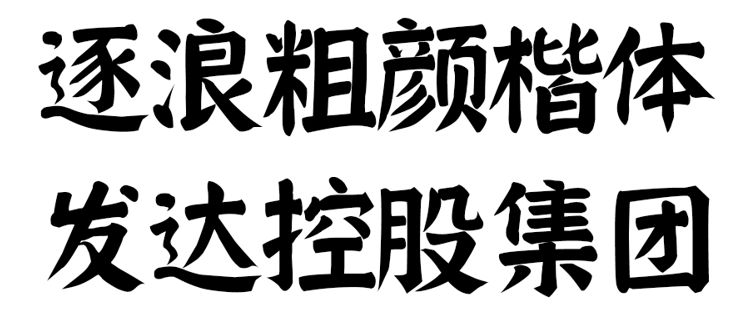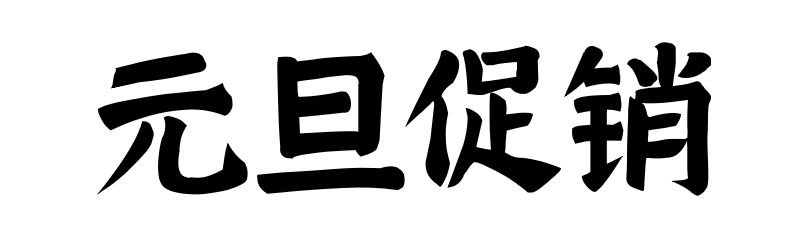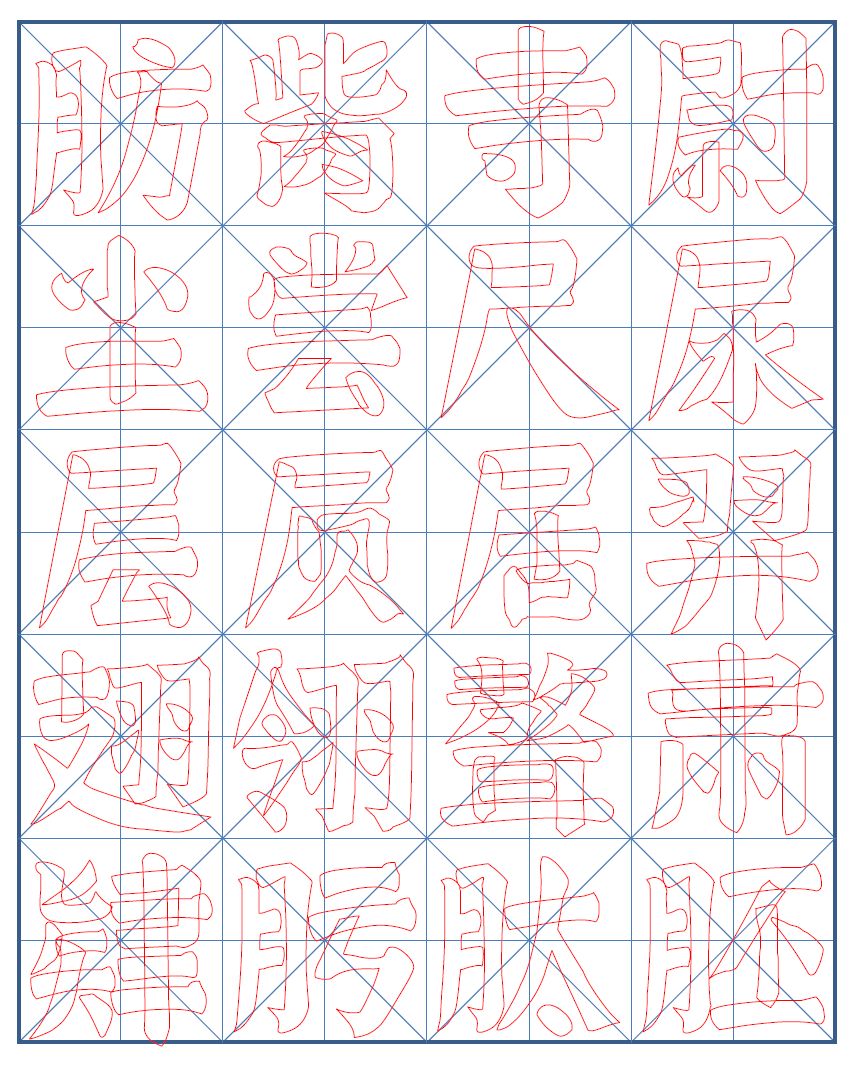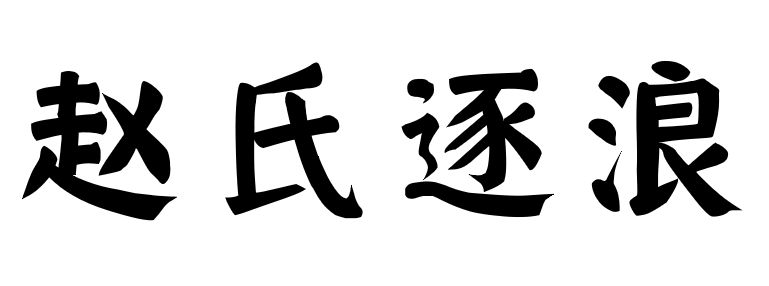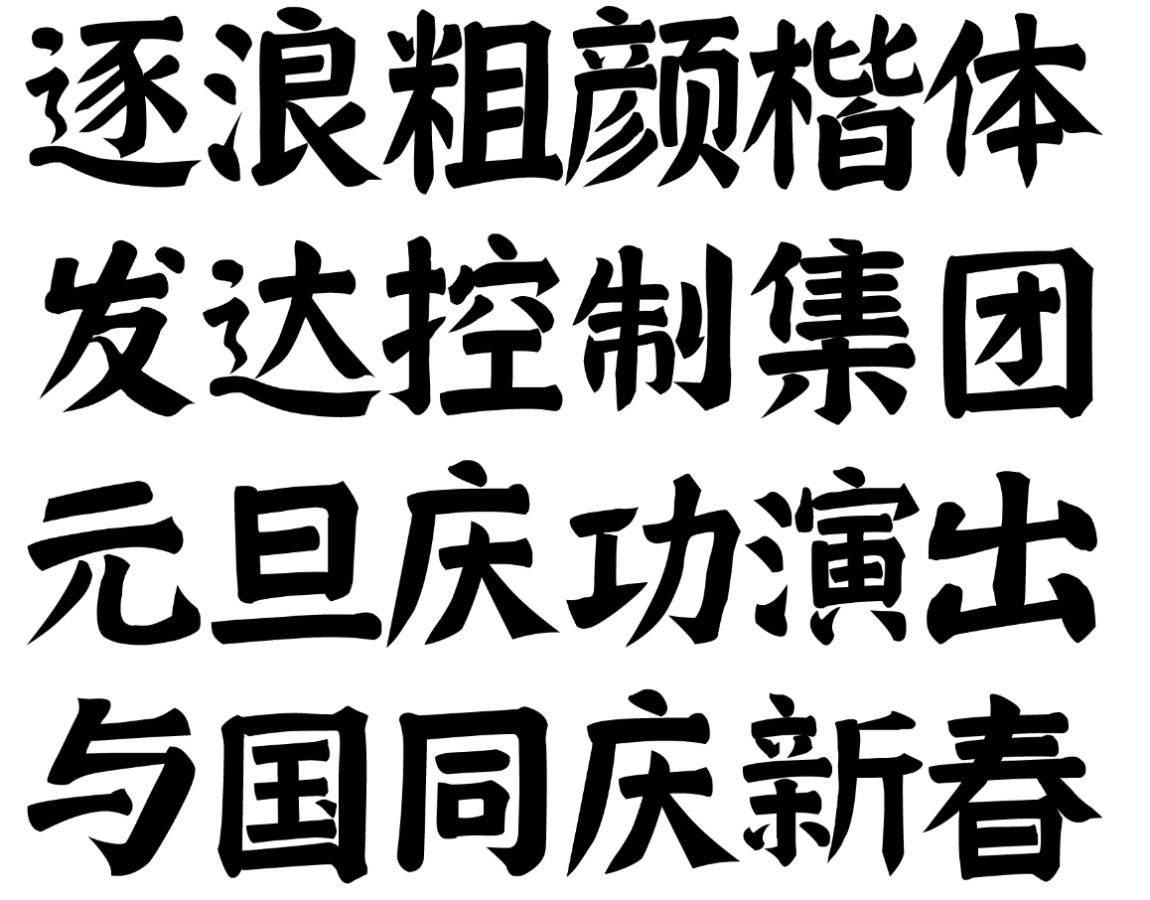
颜真卿(709年-784年8月23日),字清臣,官至吏部尚书、太子太师,封鲁郡公,人称“颜鲁公”,谥号“文忠”,世人又为颜鲁直。
颜氏书法,一直是后代法帖,其精通楷行诸体,其《祭侄稿》被后世誉为“天下第二行书”,比之行书更出名的则是楷书。
颜真卿在书学史上以“颜体”缔造了一个独特的书学境界。他的书法既以卓越的灵性系之,境界自然瑰丽;既以其坚强的魂魄铸之,境界自然雄健;又以其丰富的人生育之,境界自然阔大。初唐的欧、虞、褚、薛,只是二王书体的继承人,盛唐的颜真卿,才是唐朝新书体的创造者。”颜真卿的楷书,尤其是印岁以后的楷书,已形成一种范式,后世学习者极多,甚至有“学书当学颜”的说法,又有称之颜筋柳骨,可谓世间无二。
逐浪精颜楷,秉承颜体真风,并吸收民国颜体第一人湖南茶陵谭延闿的传世书作,进行精心制版,历时三年,终成佳作。
取法颜、柳二体精髓,字体成品效果_威严、缜密、收敛、成熟、厚重、可信的感觉
创作规范:
撇画如柳叶小刀出尖锋、略拉长
横加粗口形露耸肩
上点加粗竖画下方当为粗垂针或大刀形
竖还可以带勾
字形入笔追求传统,多采用传统的藏锋左切结构(避免右倾刀锋结构)
筋骨丰满遒劲有力
内敛如弓拉满弦
是不可多得的现代经典颜体字库。